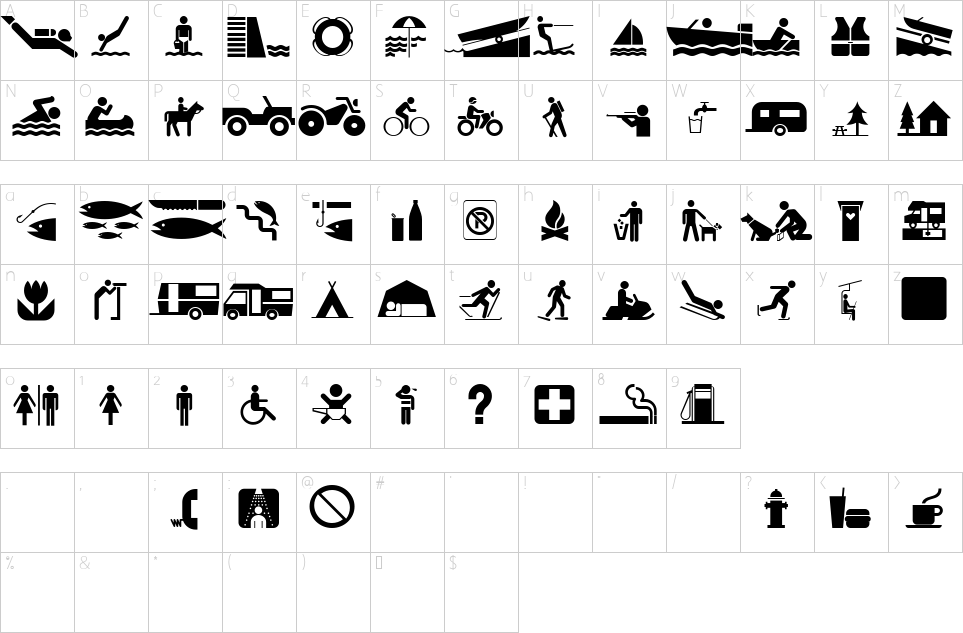
Descubra a harmonia única do Glyphyx Two Font, uma opção de graça para seus projetos digitais. Esta elegante fonte é perfeita tanto para estilos modernos quanto para designs mais clássicos, oferecendo um acabamento sofisticado em qualquer aplicação. Desenvolvida pelo designer desconhecido Nicks Fonts, a Glyphyx Two foi popularmente baixada por 5.394 pessoas. Com sua simplicidade e beleza, esta fonte é uma ótima escolha para quem procura um estilo minimalista sem perder em qualidade ou expressividade. Descubra o charme inconfundível da Glyphyx Two e revolucione a aparência de seus projetos digitais com esse recurso gráfico gratuito.